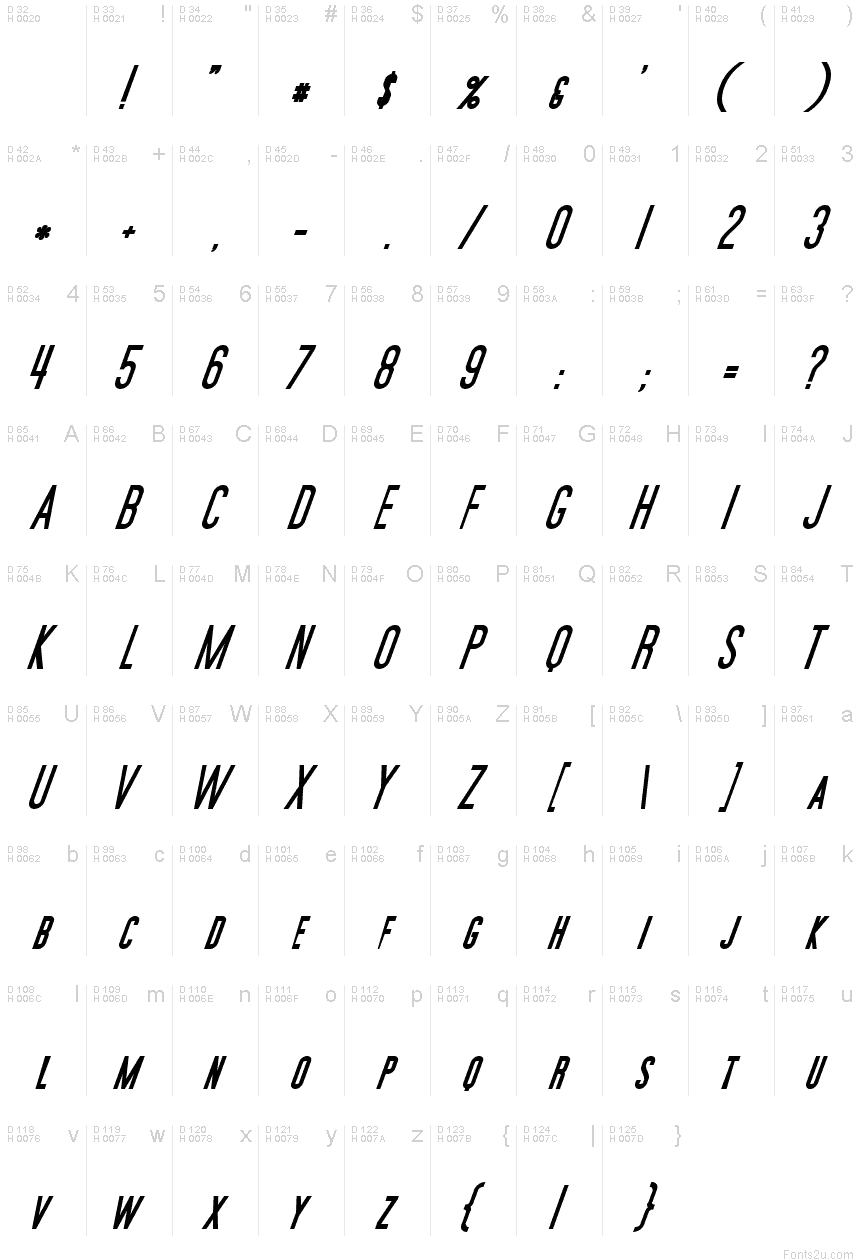
Movie Poster Bold Italic, de ShyWedge, es una tipografía sans serif gratuita con una inclinación itálica pronunciada y letras estrechas y angulares. Las formas están cortadas con diagonales nítidas y trazos largos y ascendentes, aportando al estilo de letrero un ritmo enérgico, listo para carteles.
Movie Poster Bold Italic funciona de maravilla para títulos de películas, folletos de eventos, portadas de álbumes, letreros de estilo vintage y gráficos deportivos, donde su estructura inclinada y condensada inyecta energía a los titulares cortos. Esta fuente gratuita también es ideal para logotipos y citas editoriales cuando buscas que el texto se sienta como un título diseñado y no solo como un párrafo corriente.